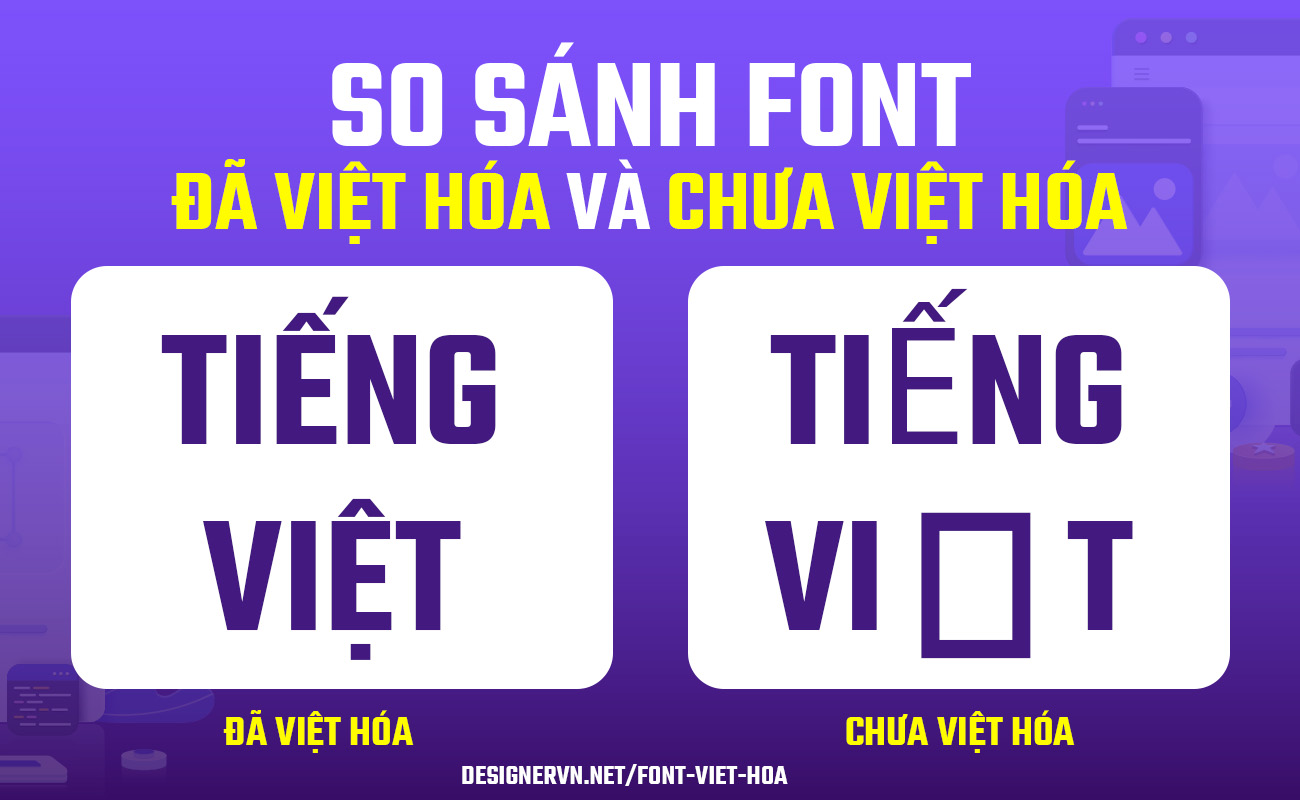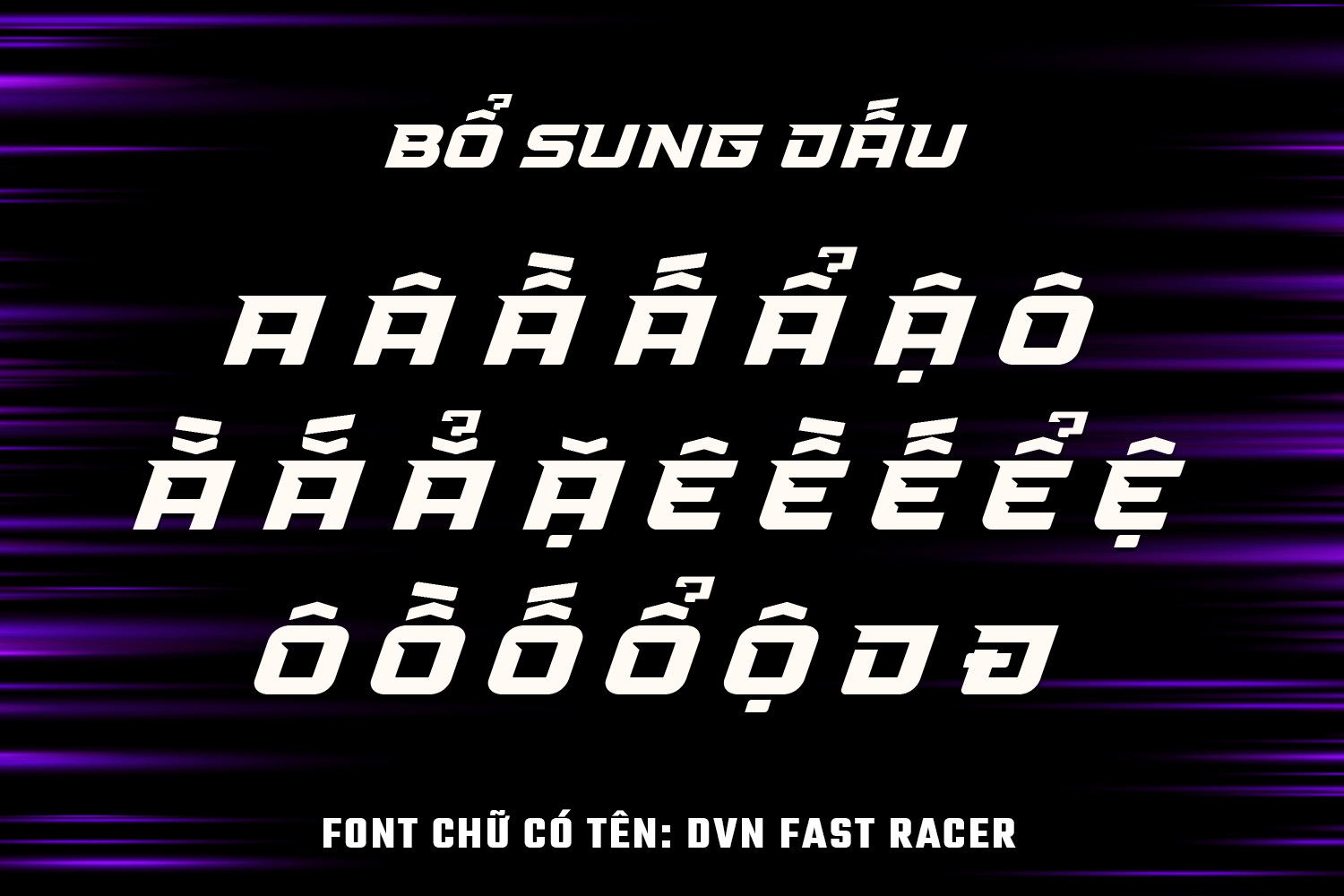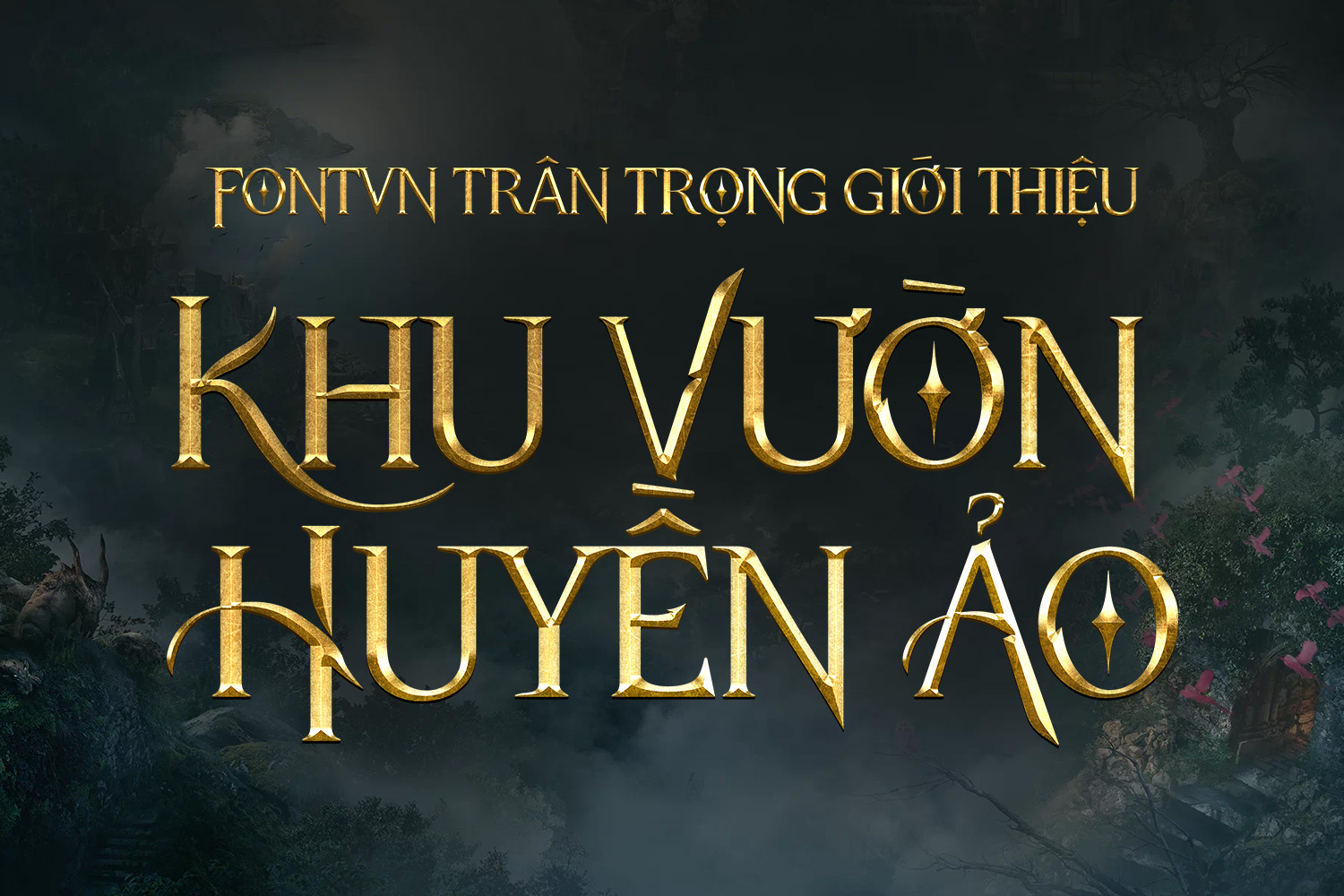
Font Việt hóa là gì ?
Font Việt hóa là thuật ngữ chỉ các bộ font đã được điều chỉnh, bổ sung đầy đủ các ký tự đặc trưng của tiếng Việt. Tiếng Việt sử dụng bảng chữ cái Latinh với dấu thanh và các ký tự đặc biệt, như: ă, â, ê, ô, ơ, đ, và các dấu thanh như sắc (´), huyền (`), hỏi (?), ngã (~), nặng (.). Điều này đòi hỏi font chữ phải hỗ trợ đầy đủ các ký tự đó để hiển thị tiếng Việt chính xác và thẩm mỹ.
Tại sao cần font Việt hóa?​
Khi sử dụng các font nước ngoài mà chưa được Việt hóa, các ký tự đặc trưng của tiếng Việt thường bị lỗi hoặc hiển thị không đúng cách, dẫn đến mất thẩm mỹ và khó đọc. Font Việt hóa đảm bảo rằng văn bản tiếng Việt có thể được hiển thị mượt mà, rõ ràng và đẹp mắt, dù là trên website, tài liệu in ấn hay các sản phẩm đồ họa khác.
Quy trình Việt hóa font​
Việc Việt hóa font bao gồm quá trình bổ sung các ký tự tiếng Việt vào font chữ gốc, điều chỉnh thiết kế để phù hợp với phong cách của font. Quy trình này thường bao gồm:
1. Bổ sung ký tự tiếng Việt: Thêm các ký tự như ă, â, ê, ô, ơ, đ và các dấu thanh.
2. Điều chỉnh kerning: Đảm bảo khoảng cách giữa các ký tự và dấu thanh không bị chồng chéo.
3. Kiểm tra thẩm mỹ: Sau khi thêm các ký tự, cần kiểm tra xem font có hiển thị đẹp và đồng bộ với các ký tự gốc hay không.
Ứng dụng của font Việt hóa​
Font Việt hóa được sử dụng rộng rãi trong nhiều lĩnh vực như:
• Thiết kế đồ họa: Để đảm bảo văn bản tiếng Việt hiển thị đúng và đẹp mắt trên các sản phẩm như poster, banner, tạp chí, phim ảnh,...
• Website và ứng dụng: Các trang web, ứng dụng cần sử dụng font hỗ trợ tiếng Việt để người dùng có trải nghiệm tốt.
• In ấn và xuất bản: Tài liệu, sách, báo chí đều cần font Việt hóa để truyền tải nội dung chính xác.
Việc sử dụng font Việt hóa giúp nâng cao chất lượng thiết kế và tăng tính chuyên nghiệp cho các sản phẩm sử dụng tiếng Việt